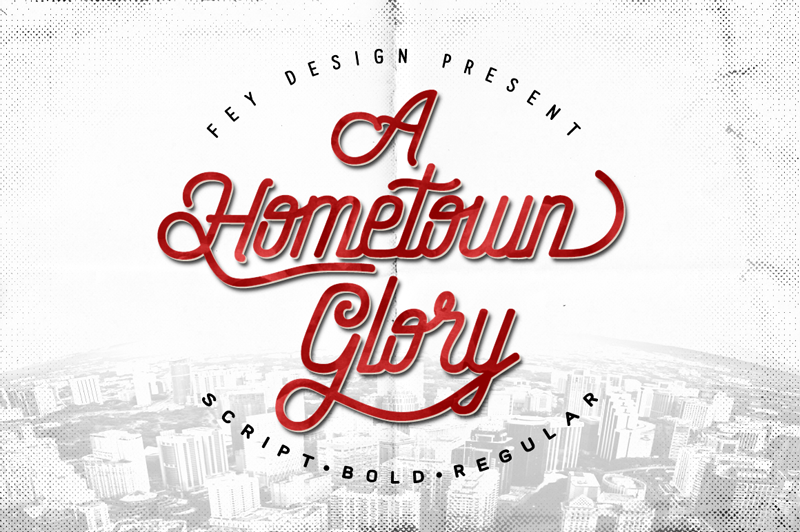
Hometown Script Font – Fonte Grátis
Hometown Script Font
A fonte Hometown Script é uma escolha perfeita para aquelas obras que desejam adicionar um toque nostálgico e retrô a qualquer projeto. Originária do estilo Blackletter, essa fonte oferece um charme esquisito que remonta à antiguidade das letras góticas. Se você está procurando por uma fonte com uma personalidade única e capaz de transformar o básico em algo especial, Hometown Script é sem dúvida a escolha certa. Ideal para aplicativos variados como cartões de aniversário, designs gráficos para livros, ou até mesmo em projetos publicitários onde queremos deixar um sopro único. Se você está buscando uma fonte com essa personalidade própria, Hometown Script é a opção certa. Crie algo que se destaca e seja lembrado, não importa o tema do seu projeto. É perfeito para manter a essência vintage de cada detalhe no design.
Designer: Fey design